Di artikel ini, Computer 1001 menyajikan 36 font untuk membuat ucapan Natal dan tahun baru; serta banner, undangan, dekorasi pesta, dan desain grafis tema Natal lainnya (wallpaper, stiker, dan label hadiah Natal).
Font Ucapan Selamat Natal & Tahun Baru
Berikut ini adalah kumpulan font Natal berupa huruf dan angka biasa.
Pada beberapa font ada hiasan gambar tema Natal yang cantik.
Font Christmas Story
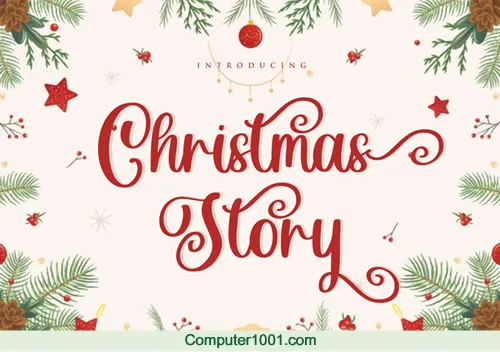
Christmas Story adalah font script yang cantik dan elegan untuk membuat tulisan selamat Natal dan tahun baru.
Font One Starry Night
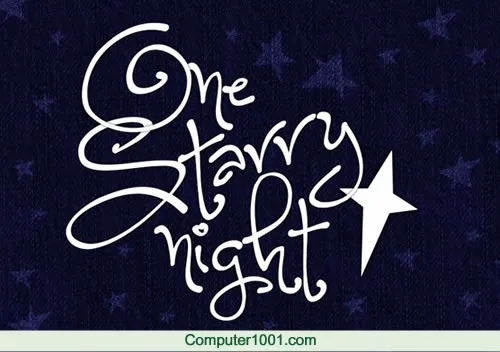
Font yang indah dengan aksen ikal yang melingkar.
Tersedia dalam bentuk huruf besar, huruf kecil, angka, huruf aksen, dan beberapa simbol lainnya.
Font Christmas Card
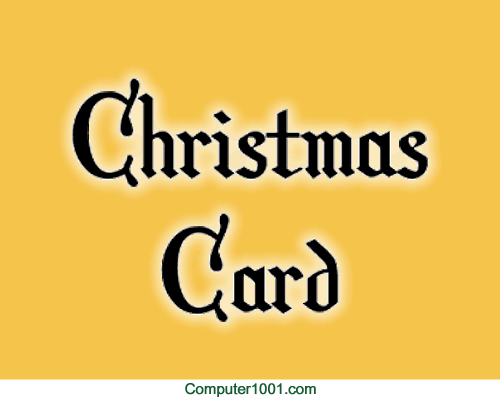
Font Christmas Card adalah font yang elegan untuk menghiasi kartu ucapan Natal, gambar postingan sosial media, dan desain lain.
Font Ucapan Natal HolLeigh Caps
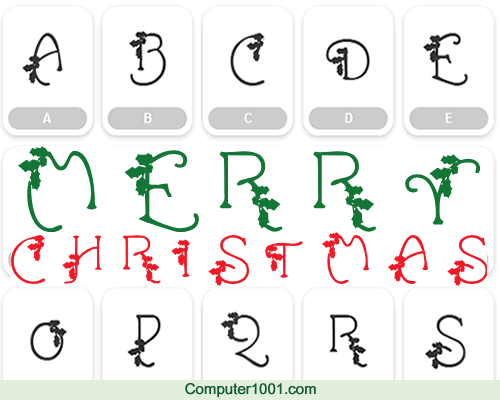
HolLeigh Caps adalah font yang cantik dengan hiasan daun holly, yang semuanya huruf besar saja.
Font Salju AlaskanNights
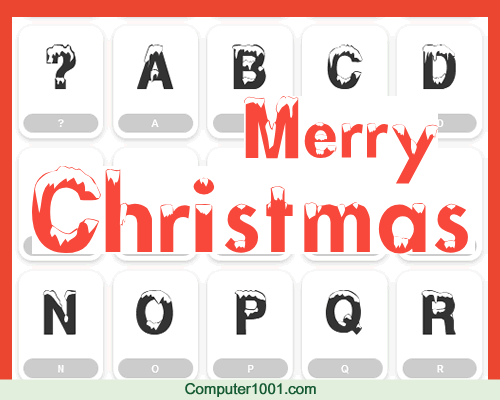
AlaskanNights adalah font yang semua karakternya tertempel salju sehingga memberikan tampilan yang cantik.
Dapat digunakan untuk membuat ucapan selamat Natal atau selamat tahun baru.
Font Natal Holly Jolly Christmas
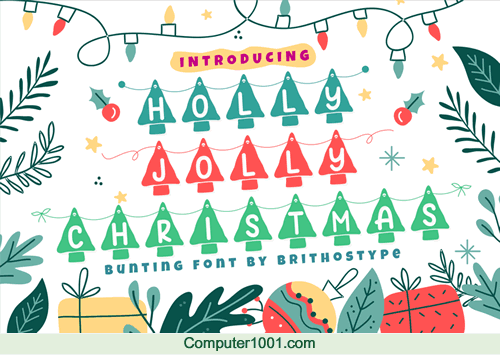
Font dengan huruf dan angka berada dalam gantungan bentuk pohon Natal yang imut.
Font Selamat Natal Merry Christmas
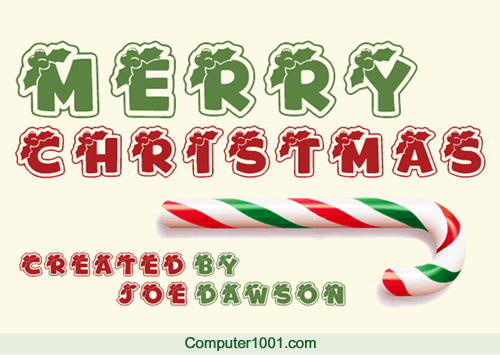
Sebagian besar karakter font Merry Christmas memiliki hiasan daun holly Natal dengan buah ceri.
Font dengan aksen outline ini terdiri dari gaya italic dan reguler.
Font Natal HOLLY&BERRIE
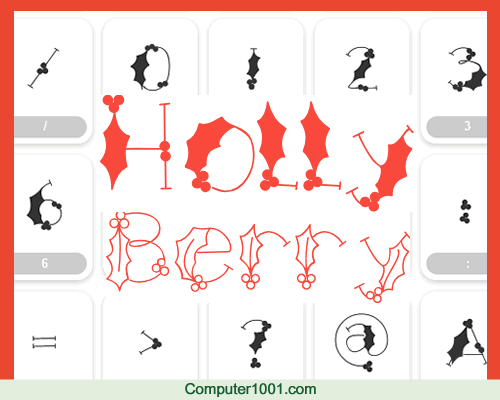
Font Holly & Berry memiliki tampilan yang cantik, dengan bentuk solid dan outline.
Font Xmas Lights
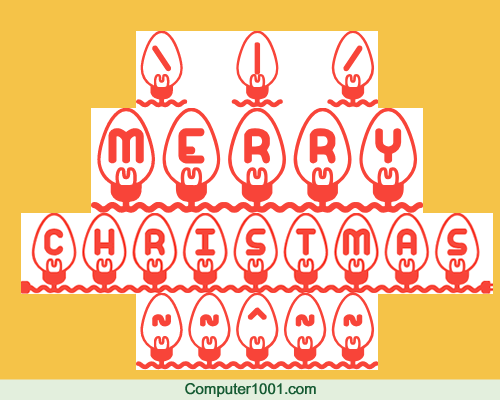
Setiap karakter font Xmas Lights berada di dalam lampu Natal yang terhubung kabel.
Gunakan karakter khusus (È É Ê Ë Ì Í Î Ï) untuk membuat bohlam lampu kosong, kabel dan colokan listrik.
Font untuk Ucapan Natal Merry Xmas St
Semua karakter font Merry Xmas berada dalam lampu Natal yang cantik berhias bintang dan simbol salju.
Font Xmas Fairy Lights
Satu lagi font yang karakternya ada di dalam lampu LED Natal, lengkap dengan hiasan kabelnya.
Font ini memiliki 2 gaya, yaitu solid dan outline.
Font Natal Pullstar-Holinight
Font Natal tebal berbentuk outline yang keren. Atasnya dihiasi daun holly dan gantungan bohlam lampu.
Font untuk Ucapan Natal X’mas?
Font dengan karakter berhiaskan berbagai ornamen Natal, yakni permen, lampu, kaos kaki, daun, dan lonceng.
Font Christmas Sparkle
Font Christmas Sparkle adalah font script aesthetic dengan hiasan bintang-bintang kecil yang berkilau.
Memiliki huruf besar dan kecil dengan total 361 karakter.
Gunakan huruf tanda aksen kapital untuk membuat huruf-huruf yang indah.
Contoh: À, È, Ì, Ò, Ù.
Font Christmas Snow
Ujung huruf font ini mirip cerobong asap yang tertutup salju.
Font Natal I Love Christmas
Font I Love Christmas adalah font yang huruf dan simbolnya bersambung.
Buat simbol Natal (pohon, pita, bintang, lampu LED) dengan menggunakan tanda garis bawah, tanda kurung [ ] dan tanda ~*^| seperti contoh pada gambar.
Font XmasAlpha
Setiap huruf font ini memiliki hiasan Natal yang lucu.
Cocok untuk membuat kartu ucapan Natal anak-anak.
Font Natal RYP Xmas Caps
Font dengan karakter di atas daun holly, yang semuanya huruf kapital.
Font Christmas Lights